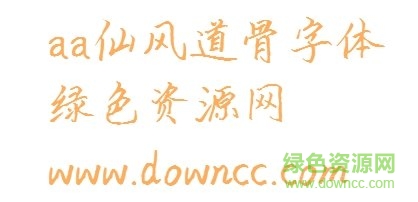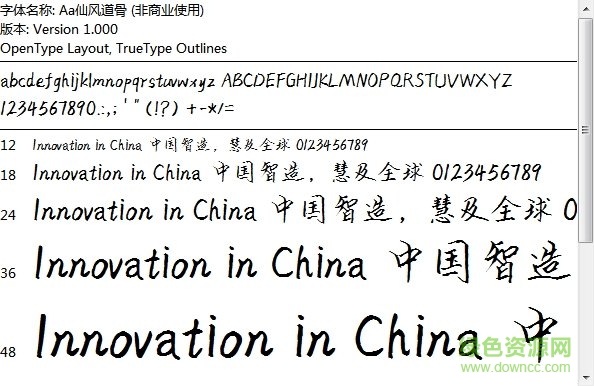
仙風(fēng)道骨字體是一款aa字體管家推出的一款古風(fēng)字體,字跡飄揚(yáng)干脆,跟人十分勁道而灑脫的視覺美感,讓人眼前一亮,喜歡的朋友就來綠色資源網(wǎng)下載收藏吧!
仙風(fēng)道骨字體看起來十分瀟灑、自由,更顯柔和清揚(yáng)之美,同樣類似手寫字體,比較適合手書、便簽、書信一類的設(shè)計(jì)圖。
仙風(fēng)道骨,形容人的風(fēng)骨神采與眾不同。本款字體如其名,給人大氣落拓的古風(fēng)之美,帶你穿越民風(fēng)淳樸而飄然忘仙的年代,感受最復(fù)古的生活氣息。